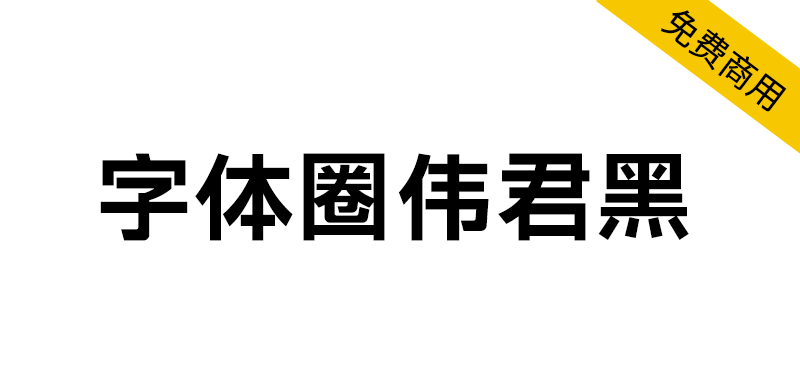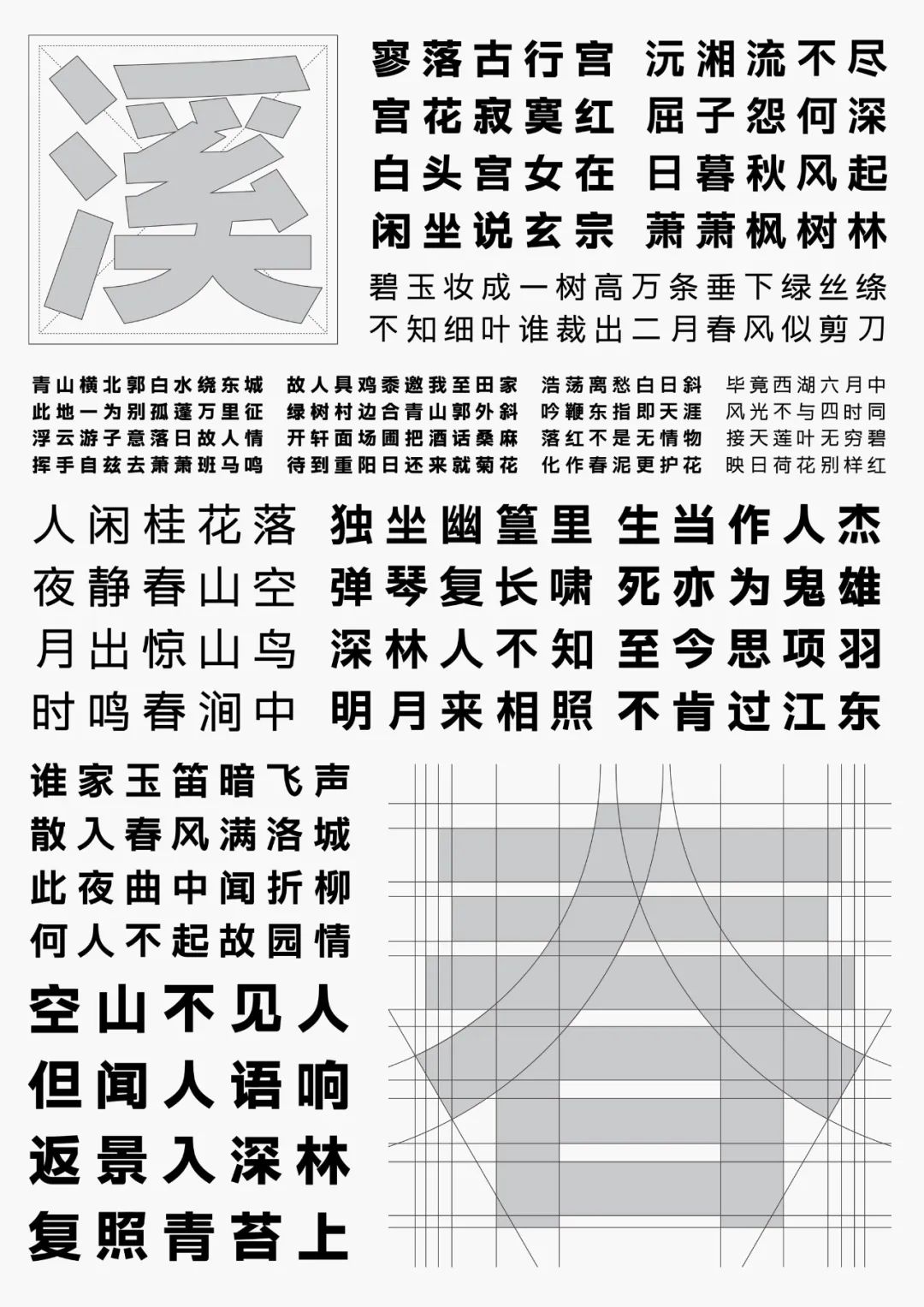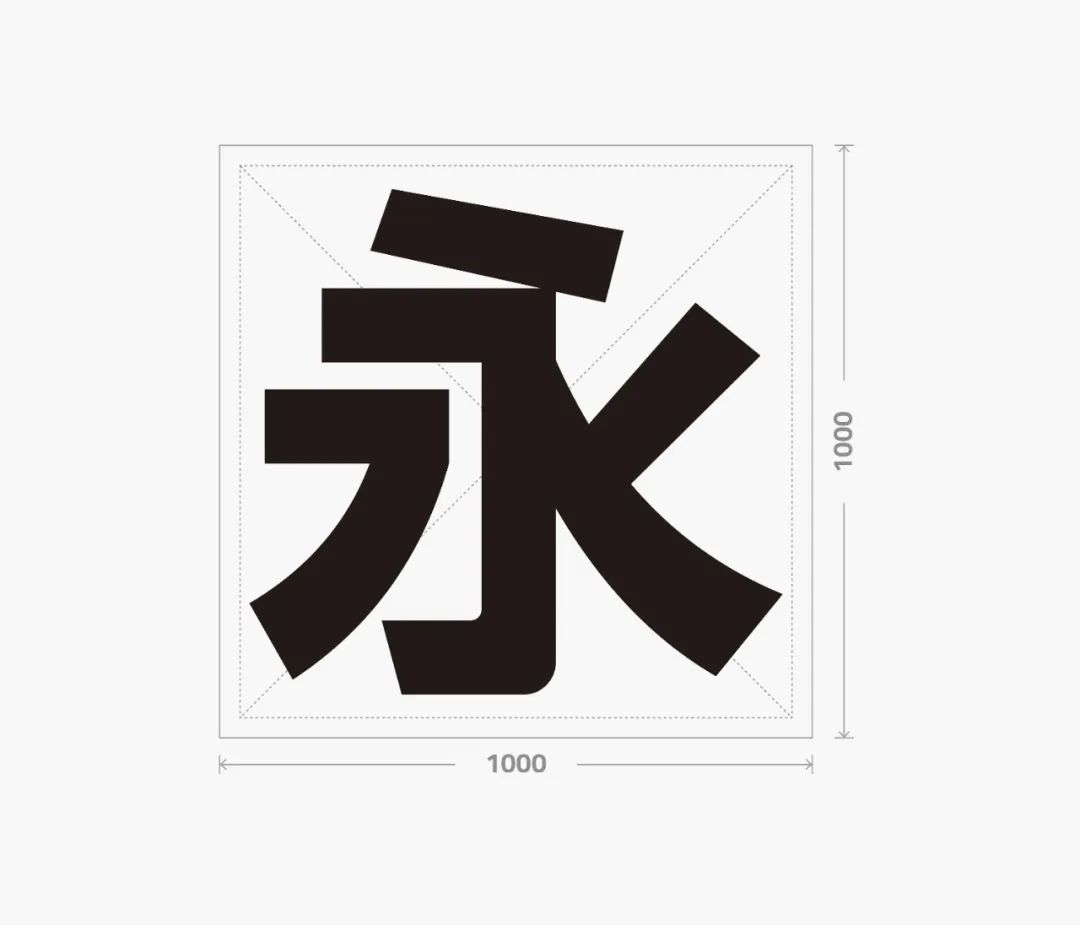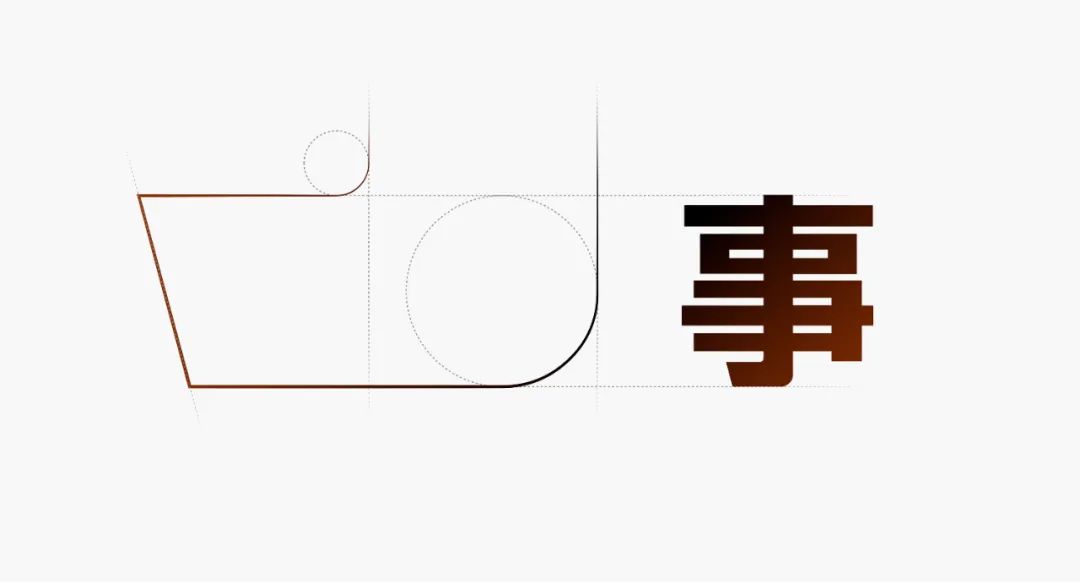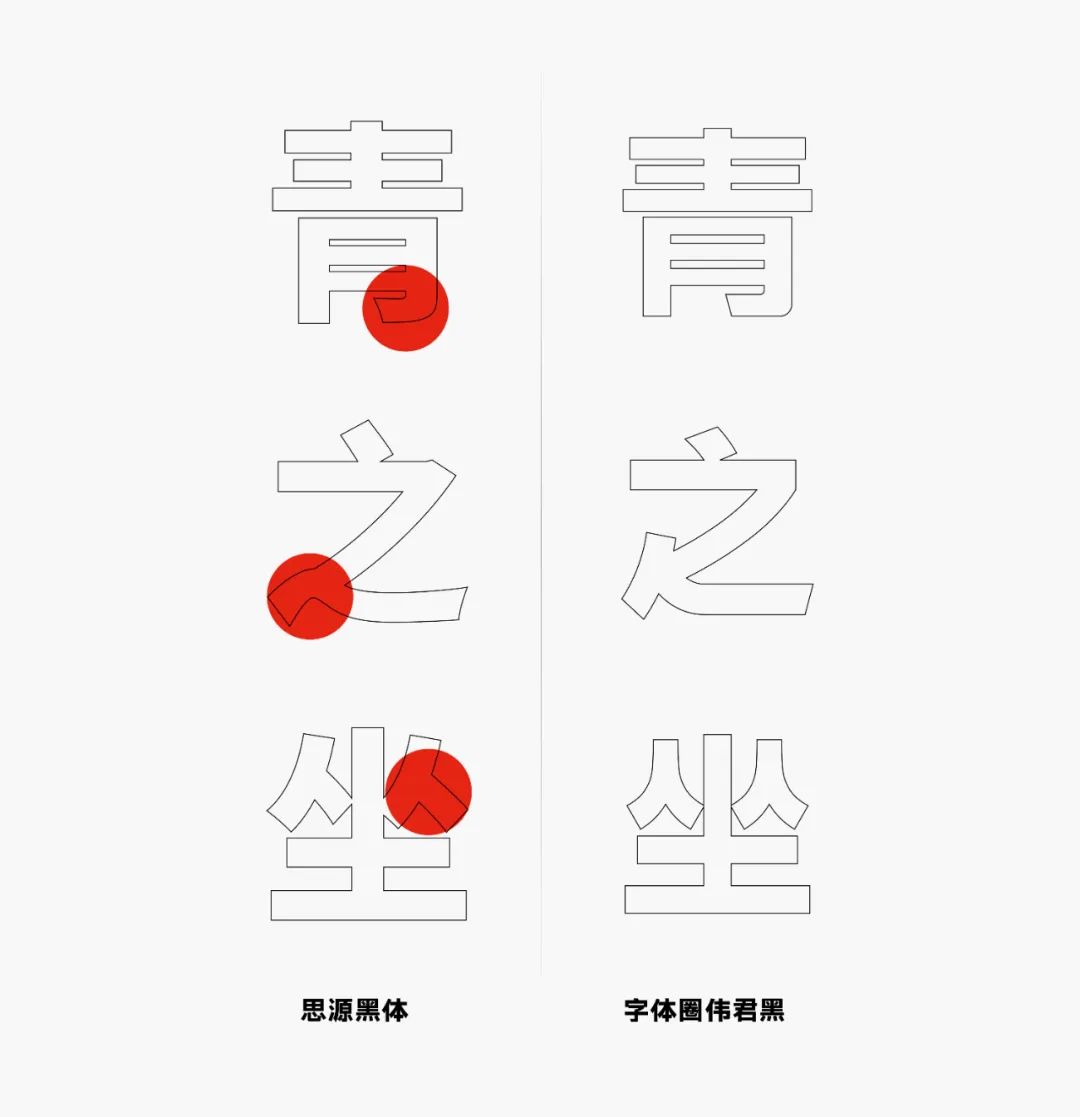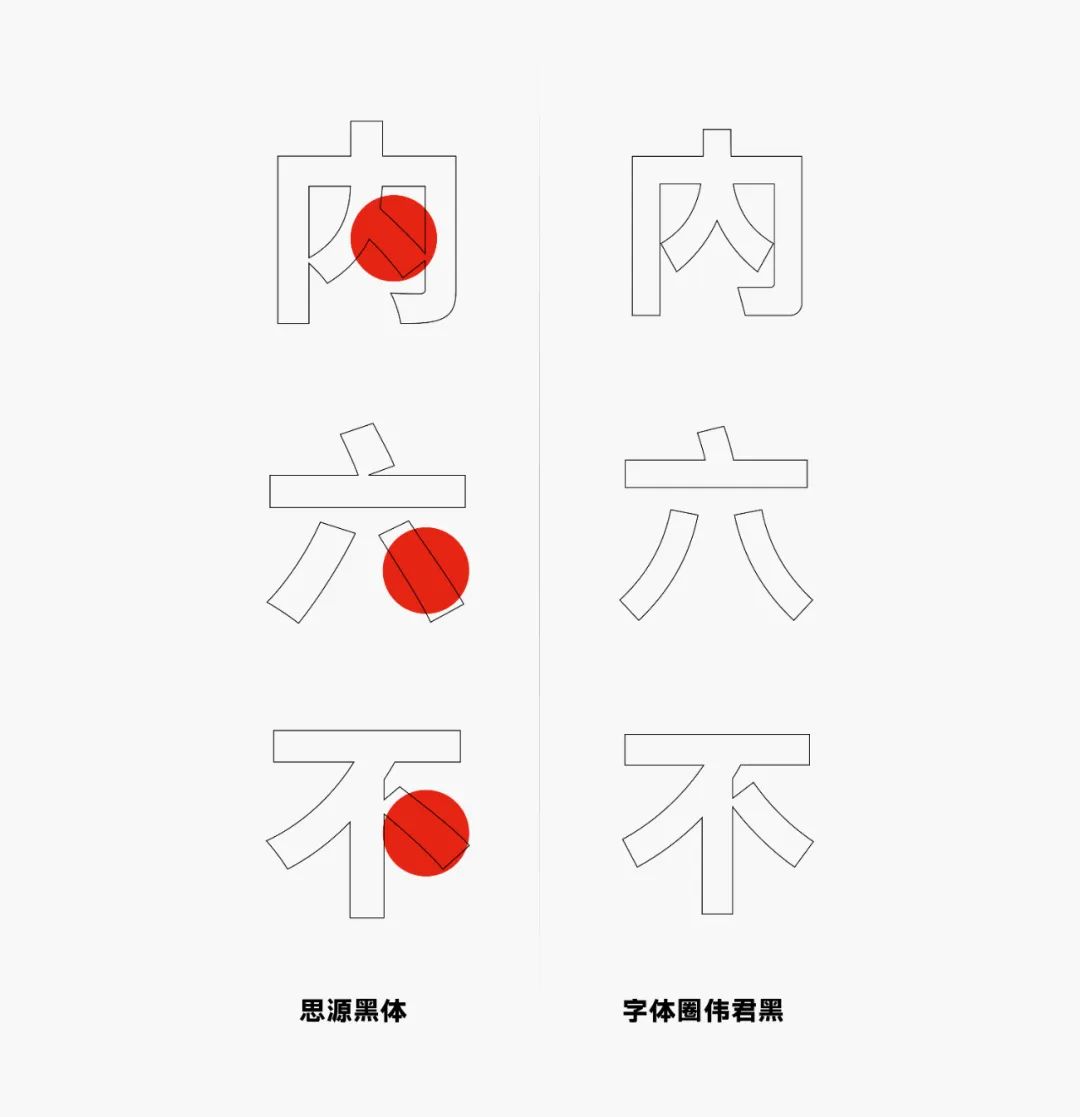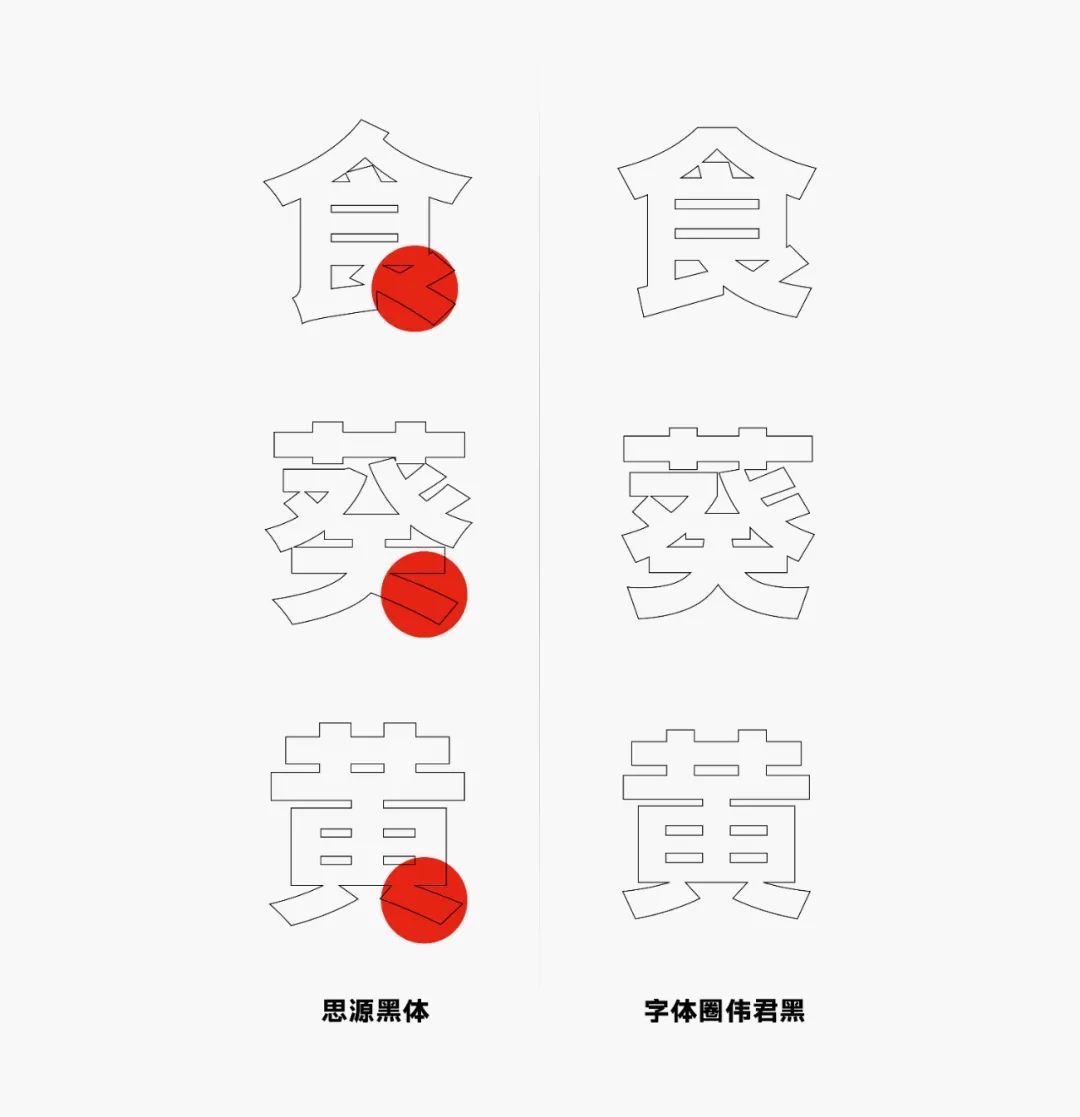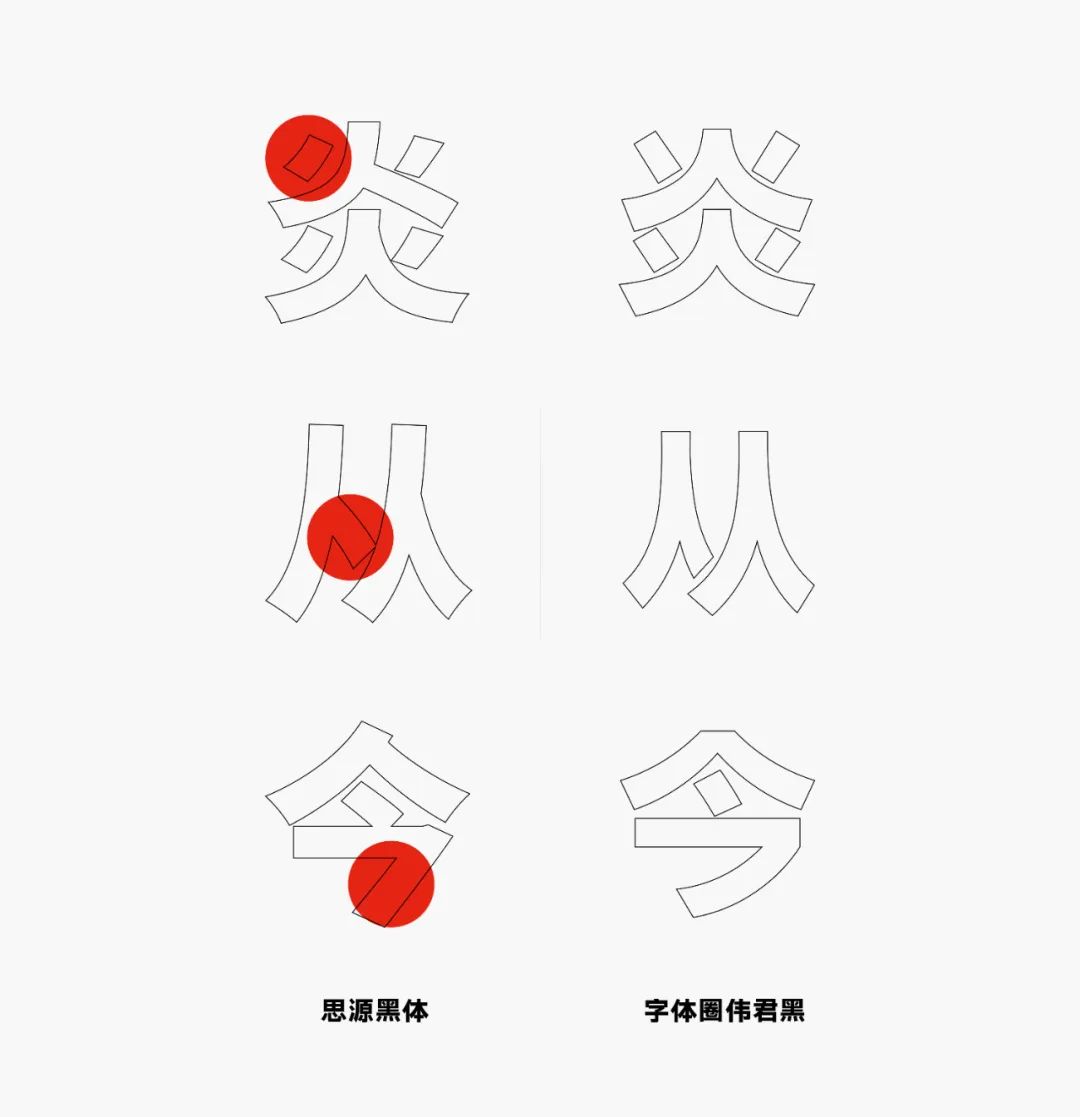
【字体圈伟君黑】适合多场景使用,例如正文排版、标题设计等
字体圈伟君黑这套字体分别有W1、W2、W3三个字重,适合多场景使用,例如正文排版、标题设计等,基本能用到字体的地方,都可以使用我们的《字体圈伟君黑》,字库现包含6763个汉字及若干个符号等,总字符7000余。
字体作者:蔡伟君 伟君黑设计师
蔡伟君,从事设计行业十余年,目前就职于深圳一家IT公司设计总监,有丰富的设计实践经验,曾服务过一些大型企业业务,诸如腾讯、OPPO、北汽、新疆农信等设计项目。
作者的话:我从事设计工作十多年,也从一个懵懂少年变为一位不惑大叔。2020年初,开始爆发疫情,公司放假,上班时间需要等通知,在家呆了一个多月,早上起来就无事可做的日子真的很难熬,回想自己设计生涯这些年,真是平平庸庸,碌碌无为,不曾做过一件有意义的事情,心中有些惭愧与落寞。
人好不容易来到这星球一趟,总该留下点什么吧,字体设计是我比较感兴趣和稍微擅长的事情,所以我想尽自己一点力,在这星球短暂的旅行留下点纪念。后来我看到邹老师发布的“字体圈欣意冠黑体”,并找到了联系方式,并表达了我想做一款免费字体的意愿,这就是我设计这款字体的心路历程。
我的话:蔡老师的想法其实跟我或者跟很多字体设计师是同样的想法,希望留下点东西在这个世界上,其他设计作品随着时间也许有一天终将会消失,但是字体是可以延续的。《字体圈伟君黑》可以说是我一点点看着做完的,我本身对正文黑体的研究不是很深,也不敢轻易去做,所以这个字体我基本没有给蔡老师很多的修改意见。
其实最开始的时候,蔡老师说很喜欢森泽黑体,想要参照森泽黑体做一款黑体字,我表示市面上的免费商用的黑体字已经很多了,可能做出来了使用者不多,没什么市场,但是蔡老师表示很喜欢森泽的笔形,对黑体字研究颇深,坚持想要做一款黑体字,最后我还是答应了,前前后后花了将近两年时间。花两年时间做一款意料不到将来的免费字体,不得不说蔡老师真的很喜欢字体,也真的很伟大。
字体风格